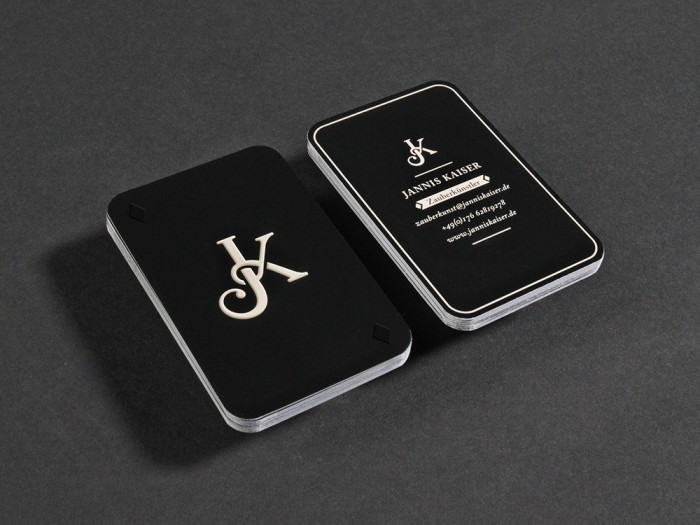
Schrift auf dem Bild gesucht
ich suche den Namen der Schrift auf diesem Bild. (Janine Kaiser, Zauberkünstler + email)
Das einzige, was ich dazu sagen kann ist, dass es die Schrift mindestens schon 1 Jahr gibt. Ich habe dieses Bild über Google Suche gefunden. Es stammt von reddit...
eine größere abbildung hast du nicht, gell? so wird’s schwierig.
aber so ähnliche schriften gibt es zu hauf: so ziemlich alles unter dem dachbegriff »renaissance-antiqua«
Aber ich hab das Logo spontan auch als sehr weiblich angesehen.  :gimmifive: